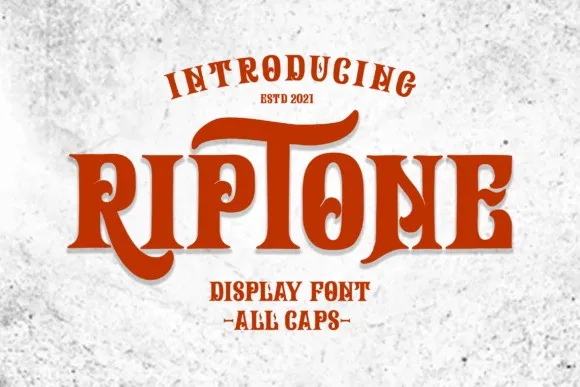
Riptone Font – Download Grátis
A Riptone Font traz um estilo inspirado nos desenhos de fim de década de 70, que é divertido, alegre e clássico sem ser sério. É uma fonte fácil de se lembrar, tornando-a um ícone na área da design gráfico. Esta fonte perfeitamente se adapta para diversos projetos criativos, como logos, cartazes, folhetos, embalagens, selos e etiquetas. Ela é especialmente útil quando você está procurando uma fonte que brinca com memórias nostálgicas do final da década de 70 e que oferece um toque atraente à sua criação. Seja para aplicações digitais ou impressas, a Riptone não decepciona. Além disso, seu uso em camisetas e roupas também permite uma conexão emocional direta com o público, criando um impacto maior em sua comunicação visual.